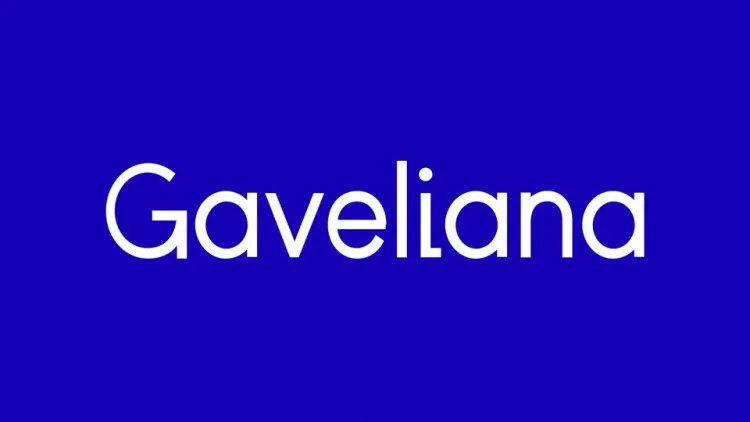
Gaveliana Font – Download Grátis
Gaveliana é uma moderna fonte sans-serif que traz um toque leve e amigável. Desenvolvida por Iordanis Passas para um projeto pessoal, a fonte Gaveliana se apresenta como uma grotesca geométrica contemporânea. Seu design original incorpora elementos de tipo serifado com uma aparência ligeiramente descontraída, criando uma mistura única que combina clareza e simplicidade. Sua geometria arredondada e linhas retas proporcionam um equilíbrio elegante, ideal tanto para headlines quanto para texto do corpo. Gaveliana é uma opção perfeita para designers buscando uma fonte leve e de bom humor que se destaca em qualquer layout. Suportando o alfabeto latino e grego, sua versatilidade se assegura para um amplo range de aplicativos. Essa fonte oferece um toque divertido ao mesmo tempo que mantém a seriedade necessária para comunicar efetivamente suas mensagens. Uma escolha inteligente para projetos digitais contemporâneos, Gaveliana não apenas se destaca por sua aparência única, mas também pelo seu suporte a duas línguas.